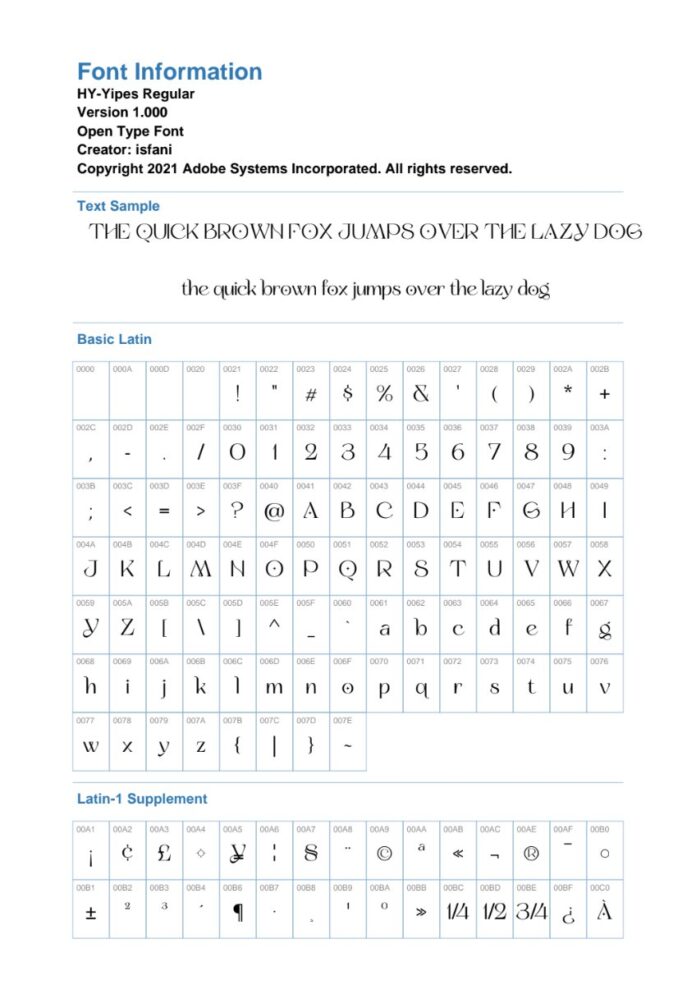
Font Chữ HY-Yipes Độc Đáo
Font Chữ HY-Yipes Độc Đáo. Khám phá font chữ HY-Yipes độc đáo, một lựa chọn hoàn hảo cho các dự án thiết kế sáng tạo. Font này mang đến sự kết hợp tinh tế giữa nét cổ điển và hiện đại, phù hợp với nhiều phong cách.
Trong thế giới thiết kế đồ họa, việc lựa chọn font chữ phù hợp có vai trò vô cùng quan trọng, quyết định đến tính thẩm mỹ và thông điệp mà tác phẩm muốn truyền tải. Hôm nay, Poster.vn hân hạnh giới thiệu đến bạn một tài nguyên font chữ đặc biệt: HY-Yipes Regular. Đây là một font chữ độc đáo, mang đến sự kết hợp hài hòa giữa nét cổ điển và hiện đại, chắc chắn sẽ làm phong phú thêm bộ sưu tập font của bạn.
Giới Thiệu Chung Về Font HY-Yipes Regular
HY-Yipes Regular là một font chữ OpenType được phát triển bởi Adobe Systems Incorporated, ra mắt vào năm 2021. Với phiên bản 1.000, font này đã nhanh chóng thu hút sự chú ý của cộng đồng thiết kế nhờ vào phong cách riêng biệt và khả năng ứng dụng đa dạng. Tên gọi ‘HY-Yipes’ gợi lên sự năng động, cá tính nhưng vẫn giữ được nét thanh lịch, tinh tế.
Đặc Điểm Nổi Bật Của HY-Yipes
• Thiết kế độc đáo: HY-Yipes sở hữu các ký tự với đường nét mềm mại, uyển chuyển nhưng vẫn có độ sắc nét cần thiết. Các chữ cái in hoa (uppercase) và in thường (lowercase) đều được thiết kế tỉ mỉ, tạo nên một tổng thể hài hòa và dễ đọc.
• Hỗ trợ đa ngôn ngữ: Font này không chỉ hỗ trợ bảng chữ cái Latin cơ bản mà còn có các ký tự Latin-1 Supplement, giúp bạn dễ dàng sử dụng trong nhiều ngôn ngữ khác nhau, mở rộng phạm vi ứng dụng.
• Tính linh hoạt cao: Dù bạn đang thiết kế logo, tiêu đề, poster, thiệp mời hay các ấn phẩm truyền thông khác, HY-Yipes đều có thể đáp ứng tốt. Sự pha trộn giữa nét cổ điển và hiện đại giúp font này dễ dàng thích nghi với nhiều phong cách thiết kế, từ tối giản đến phức tạp.
Ứng Dụng Của Font HY-Yipes Trong Thiết Kế
Với những đặc điểm nổi bật, HY-Yipes Regular là một lựa chọn lý tưởng cho nhiều loại hình thiết kế:
Thiết Kế Logo và Nhận Diện Thương Hiệu
Font HY-Yipes có thể tạo ra những logo độc đáo, mang đậm dấu ấn cá nhân. Các đường nét mềm mại nhưng vẫn mạnh mẽ của font giúp logo trở nên nổi bật và dễ nhận diện. Đặc biệt, với các thương hiệu muốn thể hiện sự sáng tạo, tinh tế và một chút phá cách, HY-Yipes là một công cụ đắc lực.
Thiết Kế Tiêu Đề và Tiêu Đề Phụ
Trong các ấn phẩm in ấn như tạp chí, sách báo, poster hay banner, việc sử dụng HY-Yipes cho tiêu đề sẽ giúp thu hút sự chú ý của người đọc ngay từ cái nhìn đầu tiên. Font này tạo ra một sự cân bằng giữa tính nghệ thuật và khả năng đọc, đảm bảo thông điệp được truyền tải một cách rõ ràng và ấn tượng.
Thiết Kế Thiệp Mời và Ấn Phẩm Sự Kiện
Với vẻ đẹp thanh lịch và độc đáo, HY-Yipes rất phù hợp để thiết kế thiệp mời cưới, thiệp sinh nhật, thiệp chúc mừng hoặc các ấn phẩm cho sự kiện đặc biệt. Font chữ này sẽ góp phần tạo nên một không khí trang trọng, tinh tế và đầy cảm xúc cho các dịp quan trọng.
Thiết Kế Website và Ứng Dụng Di Động
Trong môi trường kỹ thuật số, HY-Yipes cũng có thể được sử dụng để tạo điểm nhấn cho các tiêu đề, nút bấm hoặc các yếu tố đồ họa khác trên website và ứng dụng di động. Sự rõ ràng và tính thẩm mỹ của font giúp nâng cao trải nghiệm người dùng.
Font này phù hợp cho thiết kế logo, nhận diện thương hiệu, tiêu đề, thiệp mời, ấn phẩm sự kiện, và các yếu tố đồ họa trên website, ứng dụng di động.